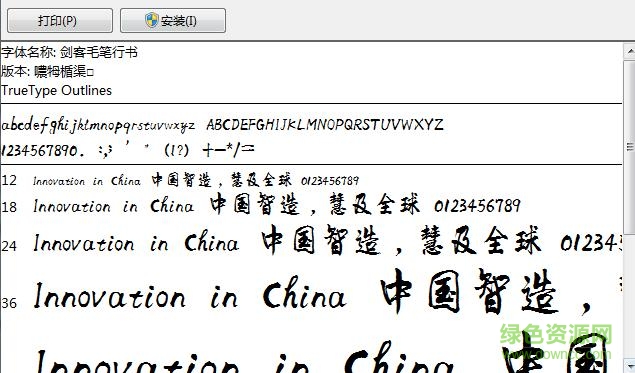
劍客毛筆行書是一款以行書為模制作的毛筆字體,字形公正有力,可用在藝術(shù)設(shè)計、廣告平面等等行業(yè)領(lǐng)域,需要書法字體的朋友歡迎下載使用!
劍客毛筆行書是一款獨具魅力的書法字體,該字體根據(jù)行書書法打造而來,字體俊逸灑脫,美觀又實用,深受藝術(shù)創(chuàng)作、排版印刷、編輯設(shè)計等行業(yè)人士喜愛!